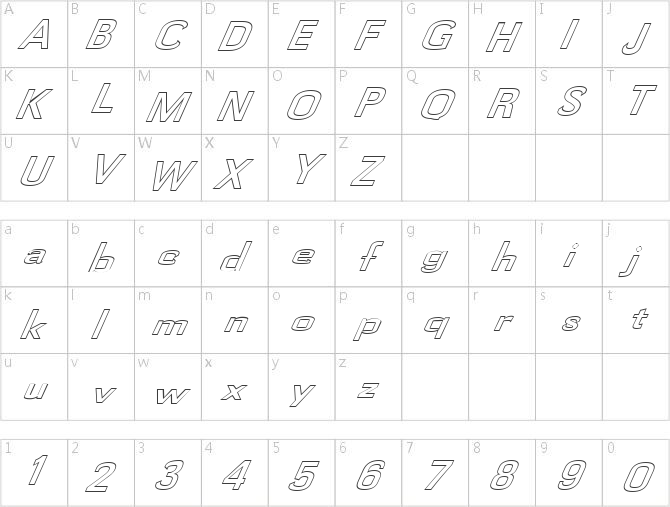
FZ BASIC 58 HOLLOW ITALIC
FZ BASIC 58 HOLLOW ITALIC介绍
FZ BASIC 58 HOLLOW ITALIC字体字库是一款让人赏心悦目、百看不厌的英文字体,适合各类广告和产品包装设计应用,字体大小0.07MB,格式为ttf字体,上传用户是晴朗,作者/版权方为未知